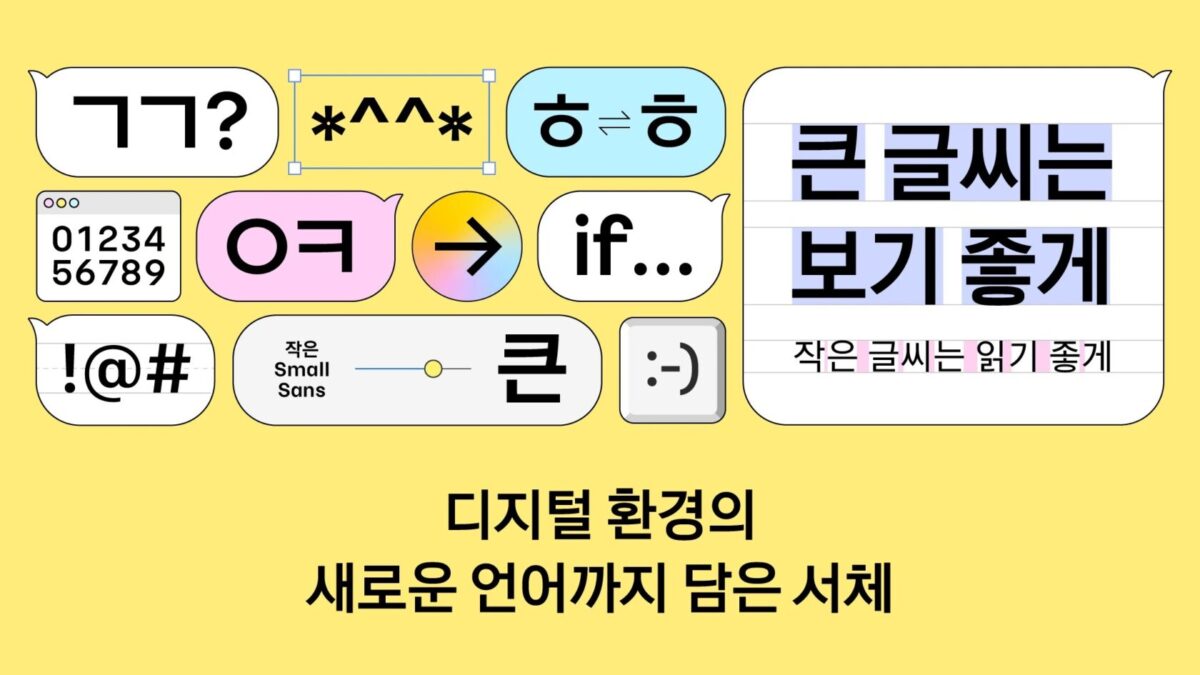
환경과 시대적 변화 반영했다… 카카오, 디지털 폰트 ‘카카오 글씨’ 무료 배포 시작
오프라인보다 디지털 기기와 환경에 더 익숙한 사용자들이 많아진 디지털 시대를 맞이해 카카오가 누구나 화면의 글을 편하게 읽고 쉽게 표현할 수 있는 디지털 폰트 ‘카카오 글씨’를 무료로 선보인다.
‘카카오 글씨’는 디지털 화면에서의 가독성과 표현방식에 최적화된 폰트로, ‘카카오 큰글씨’와 ‘카카오 작은글씨’ 두 가지로 구성됐다. 단순히 기존 폰트를 디지털로 옮긴 것이 아니라 스마트폰과 PC화면에서 최적의 읽기 경험을 제공하기 위해 새롭게 설계한 것이 특징이다.
‘카카오 큰글씨’는 제목처럼 화면에서도 또렷하고 주목도 높은 타이포그래피를 구현할 수 있는 폰트다. ‘카카오 작은글씨’는 본문이나 캡션에 적합한 폰트로, 작은 크기에서도 잘 보이도록 글자 간 간격을 넓히고 선을 정돈해 뭉개짐 없이 선명하게 보이도록 설계했다.
특히, 이번 카카오 글씨는 ‘ㅋㅋㅋ’, ‘ㅇㅇ’처럼 초성만으로 의사 표현이 자연스러워진 시대적 변화도 담아낸 것이 특징이다. 한글 초성은 일반적으로 중성, 종성과 함께 쓰이는 것을 전제로 해, 기존 폰트에선 초성만 단독으로 사용할 시 또렷하게 읽히기 어려운 한계가 있었지만, 카카오는 초성 하나만으로도 의미가 잘 전달되도록 크기를 키우고 비례를 정교하게 조절해, 초성을 단순한 글자의 일부가 아닌 독립된 하나의 글자처럼 표현할 수 있도록 변화를 줬다는 것이 회사의 설명이다.
이외에도 카카오 글씨는 특수기호로 표현하는 텍스트 이모티콘 조형도 더욱 정교하게 다듬었다. 두 개 이상의 기호나 글자 조합을 하나의 형태로 자동 변환하는 ‘리가처(Ligature)’ 기능을 통해, 특정 기호를 입력하면 정돈된 형태의 이모티콘으로 바뀌어 글자이지만 마치 표정처럼 보이는 생동감 있는 감정 표현이 가능하다.
예를 들어 ‘:-D’와 같은 웃는 이모티콘은 폰트에 따라 D의 위치나 크기로 인해 어색해보이기 쉬웠지만, 카카오 글씨는 이모티콘 전체를 정돈된 형태로 출력해 깔끔하고 균형감 있는 이모티콘 사용을 돕는다. 또한 ‘->’처럼 자주 쓰는 기호 조합은 입력 즉시 자동 변환해줌으로써 특수문자를 따로 찾아야 하는 불편함을 없앴다.
신영섭 카카오 BX디자인 리더는 “카카오 글씨는 우리가 매일 마주하는 스마트폰 등 디지털 화면에서 최적의 가독성과 표현력을 제공하기 위해 탄생했다” 며 “앞으로도 변화하는 시대의 소통 방식을 이해하고 이를 반영하는 폰트로 더 풍부한 디지털 표현 문화에 기여하겠다”고 덧붙였다.